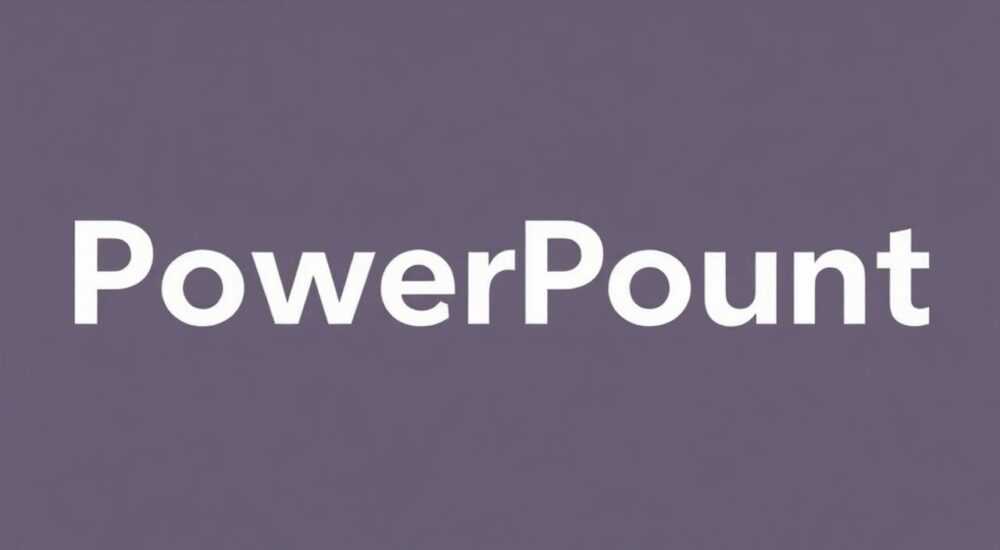
Как поменять шрифт в powerpoint
В PowerPoint — одном из самых популярных инструментов для презентаций в бизнесе, образовании и творческих проектах — шрифт играет ключевую роль не только в эстетике, но и в восприятии информации. Неправильный выбор шрифта может сделать слайд перегруженным, нечитаемым или даже профессионально небрежным. Многие пользователи сталкиваются с трудностями при попытке изменить шрифт: где найти настройки, как применить изменения ко всему документу, как сохранить единый стиль? Ответы на эти вопросы — не просто технические инструкции, а основа эффективной визуальной коммуникации. Правильно оформленная презентация повышает доверие аудитории на 47% (по данным исследования Harvard Business Review), а согласованность шрифтов — один из ключевых факторов этого доверия.
Как поменять шрифт в PowerPoint: пошаговая инструкция
Изменение шрифта в PowerPoint — одна из самых базовых, но при этом критически важных операций. Даже небольшой сдвиг в типографике может кардинально изменить восприятие вашего сообщения. Чтобы начать, откройте презентацию и перейдите на слайд, который нужно отредактировать.
Выделите текст, который требует изменения. Можно выбрать один абзац, весь текст в текстовом поле или даже несколько текстовых блоков, удерживая клавишу Ctrl. Если вы хотите изменить шрифт в заголовке, кликните на него — не нужно выделять каждый символ, достаточно просто щёлкнуть внутри текстового поля.
Теперь перейдите на вкладку «Главная» в верхней панели инструментов. В группе «Шрифт» вы увидите выпадающий список с названиями доступных шрифтов. Кликните по стрелке и выберите нужный — например, «Calibri», «Arial» или «Segoe UI». Как только вы сделаете выбор, изменение применится мгновенно. Если вы не видите нужный шрифт — возможно, он не установлен в системе. В этом случае его нужно установить отдельно через Windows или macOS.
Если вы работаете с макетом слайда, а не с отдельным текстом, убедитесь, что вы не выделили элементы, которые защищены шаблоном. В таком случае изменения могут не применяться — о чём пойдёт речь далее.
Как выбрать шрифт по размеру и стилю
Помимо самого названия шрифта, на вкладке «Главная» вы найдёте другие параметры: размер, цвет, выравнивание. Для презентаций рекомендуется использовать размер не менее 24 пунктов для основного текста и 32–44 — для заголовков. Меньшие размеры теряются на экране, особенно при проекции.
Стили — полужирный, курсив, подчёркивание — применяются через кнопки с жирной буквой B, курсивным I и подчёркнутым U. Не переусердствуйте: курсив и подчёркивание — инструменты акцента, а не основного стиля. Их чрезмерное использование превращает текст в «визуальный шум».
Как изменить шрифт во всей презентации сразу
Ручная смена шрифта на каждом слайде — утомительно и ненадёжно. Особенно если презентация состоит из 20+ слайдов. В PowerPoint есть мощный инструмент — «Изменить шрифты», который позволяет задать единый типографический стиль для всей презентации.
Перейдите на вкладку «Дизайн». В правом нижнем углу группы «Настройка» найдите маленькую стрелочку — нажмите её, чтобы открыть панель параметров дизайна. Здесь вы увидите пункт «Шрифты». Кликните по нему — появится список предустановленных комбинаций, таких как «Каллиграфия», «Современный» или «Классический».
Если вы хотите создать собственный шрифтовый стиль, выберите «Создать новые шрифты». Откроется окно, где можно задать шрифт для заголовков и для тела текста. Например, заголовки — «Montserrat Bold», текст — «Lato Regular». Назовите свою комбинацию (например, «Корпоративный стиль 2026») и нажмите «Сохранить». Теперь все новые слайды будут использовать этот стиль, а существующие — автоматически обновятся.
Этот метод особенно полезен при работе с командой: один человек задаёт шрифтовую систему, и все участники работают в едином стиле без риска рассогласованности.
Как применить шрифты к уже существующим слайдам
Если вы уже создали презентацию и хотите «навести порядок», просто выберите нужную комбинацию шрифтов в меню «Шрифты» — и PowerPoint автоматически заменит все соответствующие тексты. Важно: если в слайдах использовались шрифты, не входящие в новую схему, они останутся без изменений. Поэтому перед применением проверьте, нет ли «свободных» текстовых блоков, которые не привязаны к макету.
Шрифтовые стили: полужирный, курсив, подчёркивание
Шрифтовые стили — это не просто украшения. Они формируют иерархию информации. Полужирный шрифт — лучший инструмент для акцента на ключевых словах. Курсив — для цитат, терминов или второстепенных пояснений. Подчёркивание в презентациях — почти всегда избыточно: в цифровом формате оно ассоциируется с гиперссылками, что вводит аудиторию в заблуждение.
PowerPoint позволяет применять стили через кнопки на панели «Главная», но есть и более точный способ — через диалоговое окно «Шрифт». Выделите текст, нажмите Ctrl+D (или щёлкните правой кнопкой → «Шрифт»). Откроется окно с расширенными настройками: тень, подчёркивание, эффекты, позиция (надстрочный/подстрочный). Здесь можно задать, например, тонкую тень под заголовками — это добавит глубину без перегрузки.